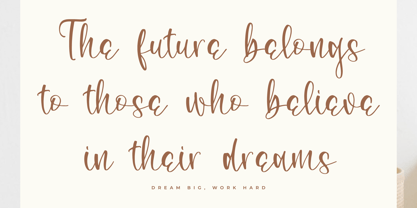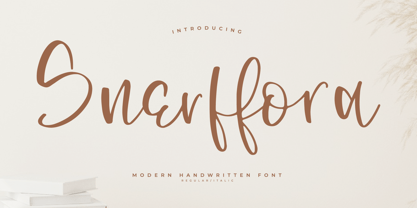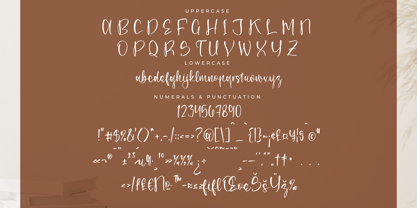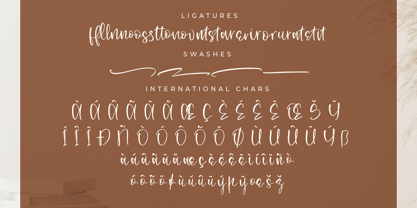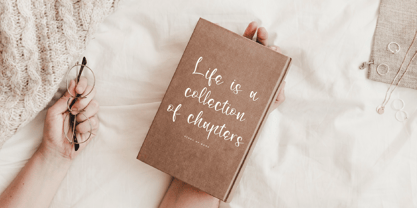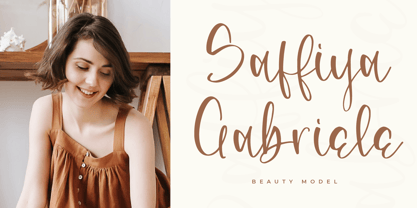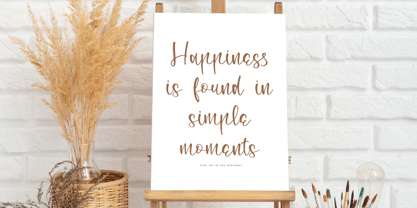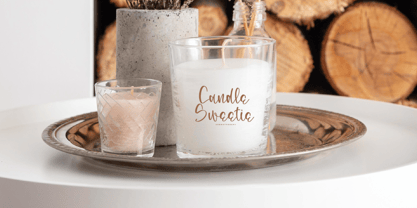
Snerffora
Die Schriftfamilie Snerffora wurde von Heru Utama Putra entworfen und von Letterena Studios veröffentlicht. Snerffora enthält 2 Stile und Familienpaketoptionen. Mehr über diese Familie
Snerffora – Modern Handwritten Font , from Letterena, is a Luxury Script font, suitable for any projects such as: logos, branding projects, homeware designs, product packaging, mugs, quotes, posters, shopping bags, t-shirts, book covers, name card, invitation cards, greeting cards, label, photography, watermark, special events, and all your other luxury and beautiful projects that need a Luxury serif taste.